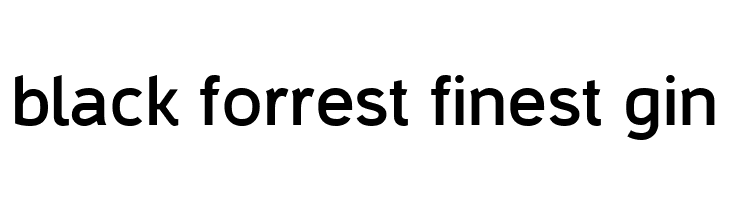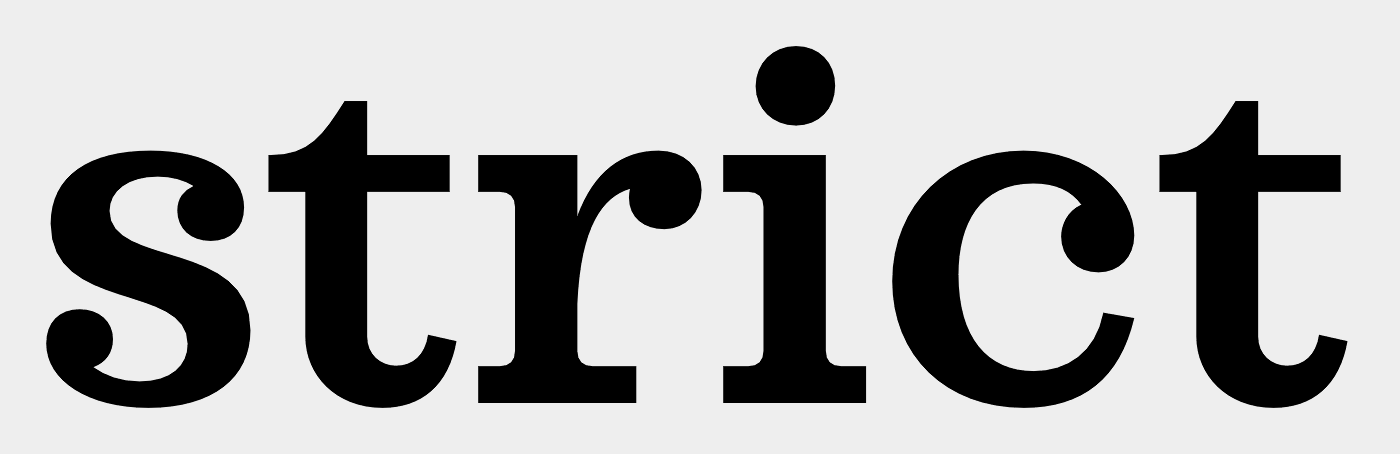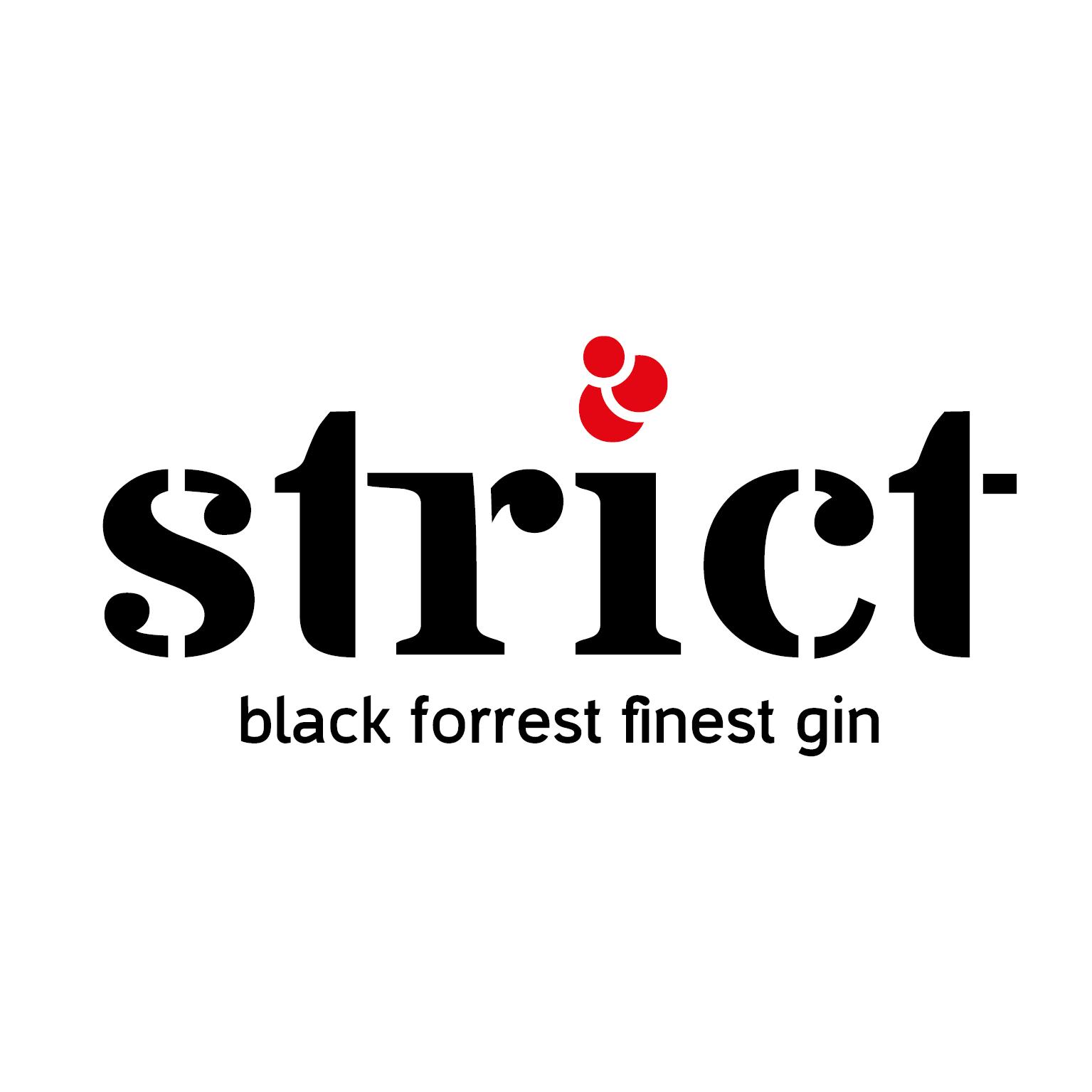
Schrift eines Logos gesucht (strict)
ich suche zwei Fonts eines Logos das ich selbst mal vor Jahren erstellt habe. Ich finde die Schriftart einfach nicht mehr.
An dem Wort "strict" hatte ich damals wohl auch ein wenig "rumgeschnippelt" : )
Würde mich freuen wenn mir jmd helfen kann. Whatthefont, etc. spuckt dazu nichts aus.
Ich weiß ja nicht, wie viel du geschnippelt hast, aber die käm schon in die Nähe:
Danke Bertel. Die ist es zwar wahrscheinlich nicht (am unteren Fuß von r und i habe ich nicht geschnippelt *g*) aber das hilft auf alle Fälle schon mal sehr weiter!